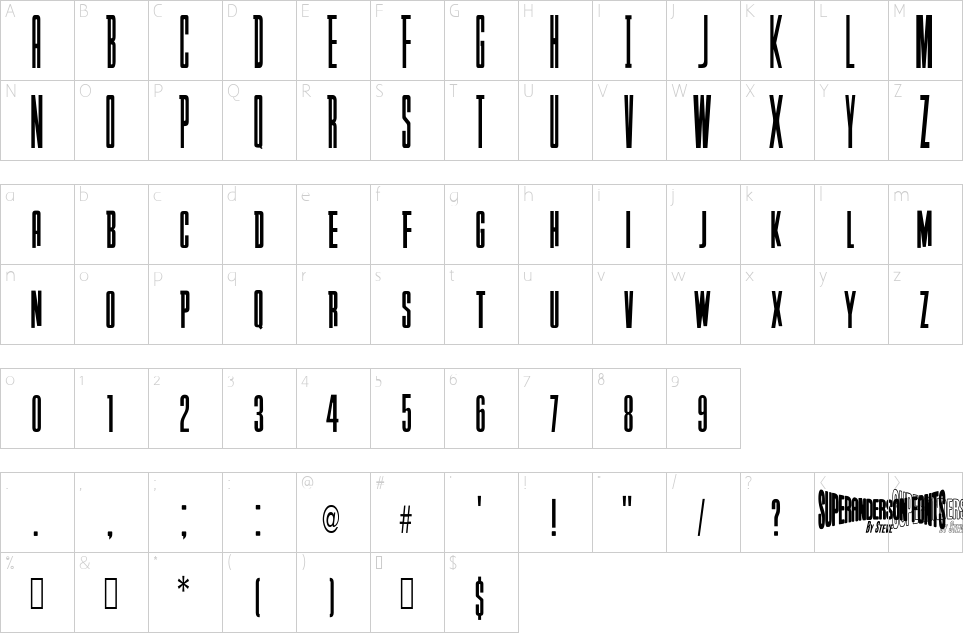
Anderson Captain Scarlet Font
A fonte Anderson Captain Scarlet é uma escolha perfeita para quem busca uma escrita arrojada e vibrante para seus projetos gráficos em português. Desenvolvida por Steve Ferrera, esta fonte está disponível tanto para sistemas Windows quanto para Mac. Ela carrega uma essência que faz dela uma escolha elegante para aplicações que valorizam um toque de elegância e originalidade. Com seu design arrojado e colorido, Anderson Captain Scarlet é uma ótima opção para personalizar sua marca ou criar design editorial que destaca-se. Até agora, Anderson Captain Scarlet tem sido descarregada mais de 14.230 vezes, indicando a sua popularidade entre designers e criadores de conteúdo. Se procura uma fonte moderna e versátil, sem dúvida Anderson Captain Scarlet é uma opção que não pode ser esquecida.
Mapa de caracteres da fonte Anderson Captain Scarlet Font